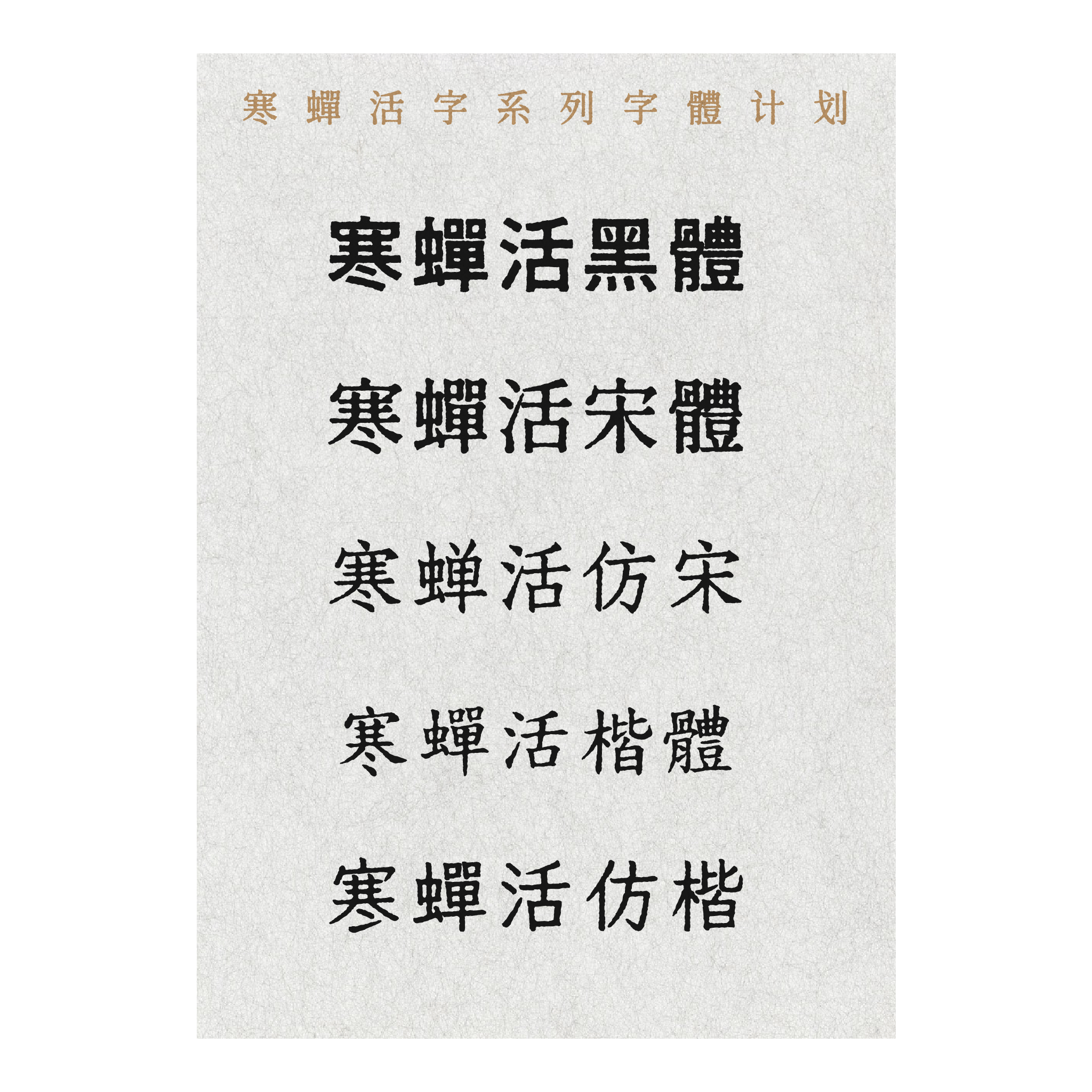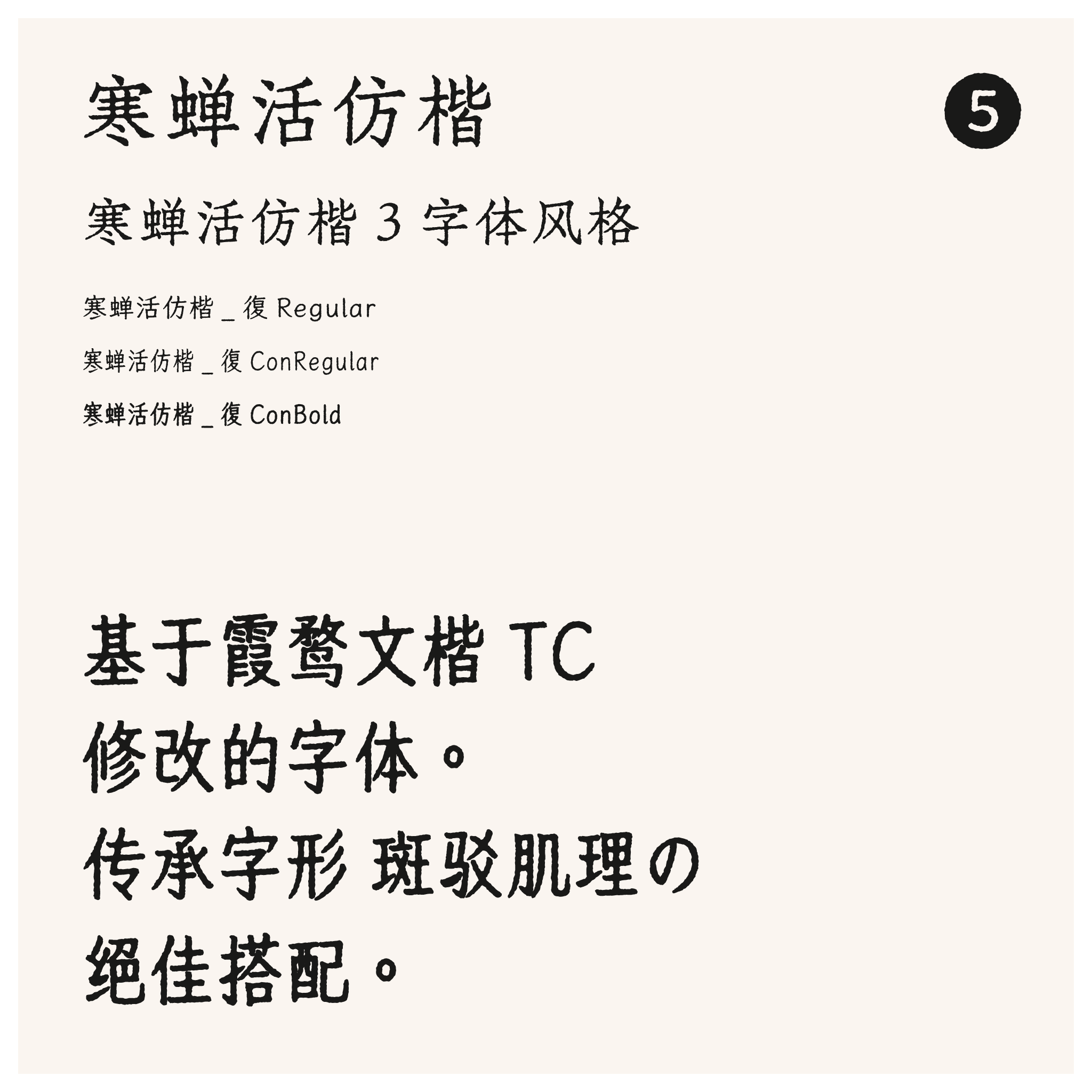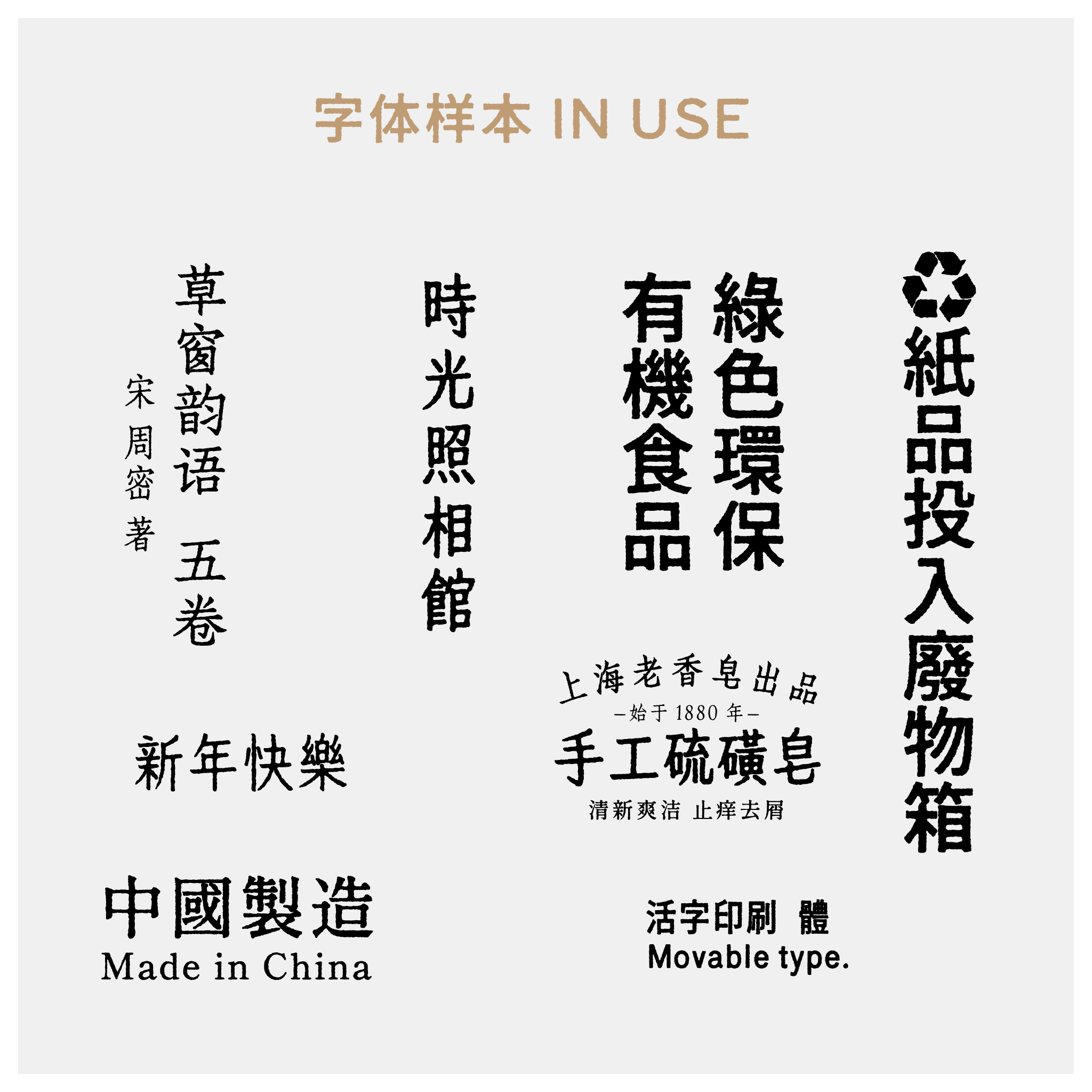
寒蝉活仿楷,作为一款基于备受赞誉的霞鹜文楷TC进行深度优化与再创作的字体,不仅完整继承了原字体那份端庄稳重而又不失灵动的骨架结构,更在其核心设计中融入了独特的美学追求。它着重于对笔画肌理进行精心处理,刻意模拟出历经岁月洗礼后碑版刻字所特有的斑驳、自然磨损的质感。这种细节上的锤炼,使得每一个字符在屏幕或纸张上呈现时,都仿佛承载着时间的痕迹与书卷的沉香,赋予了文字一种古朴而鲜活的生命力。
因此,寒蝉活仿楷堪称是追求传统韵味与现代表达相结合之设计的绝佳搭配。无论是用于需要传达历史厚重感的文化类出版物、诗词标题,还是为数字界面增添一抹雅致的复古气息,亦或是作为品牌标识传递匠心与底蕴,它都能以其卓越的质感与兼容性,为整体视觉效果增添不可多得的层次与深度,让文字的呈现超越单纯的信息传递,升华为一种细腻的情感与审美表达。